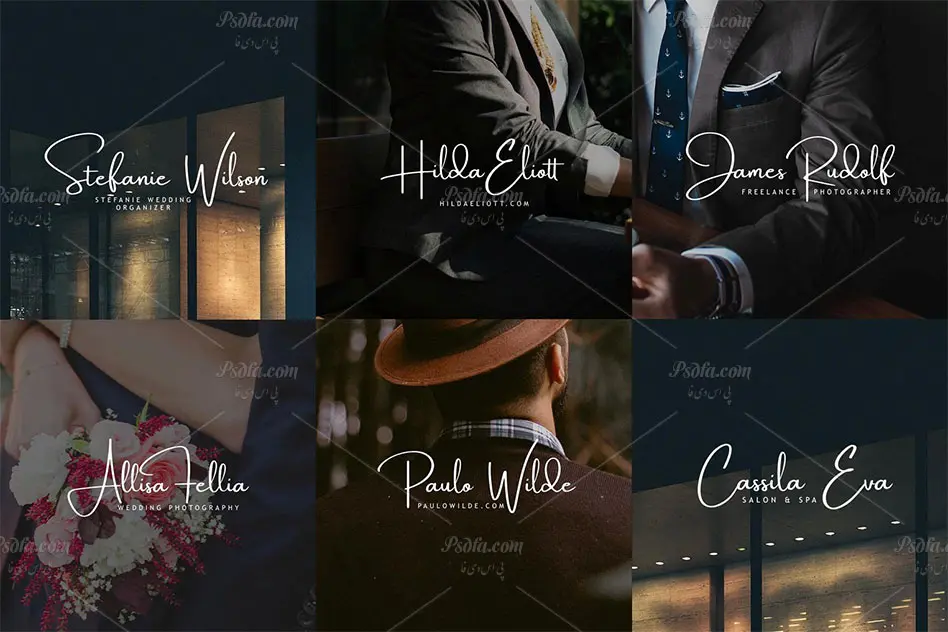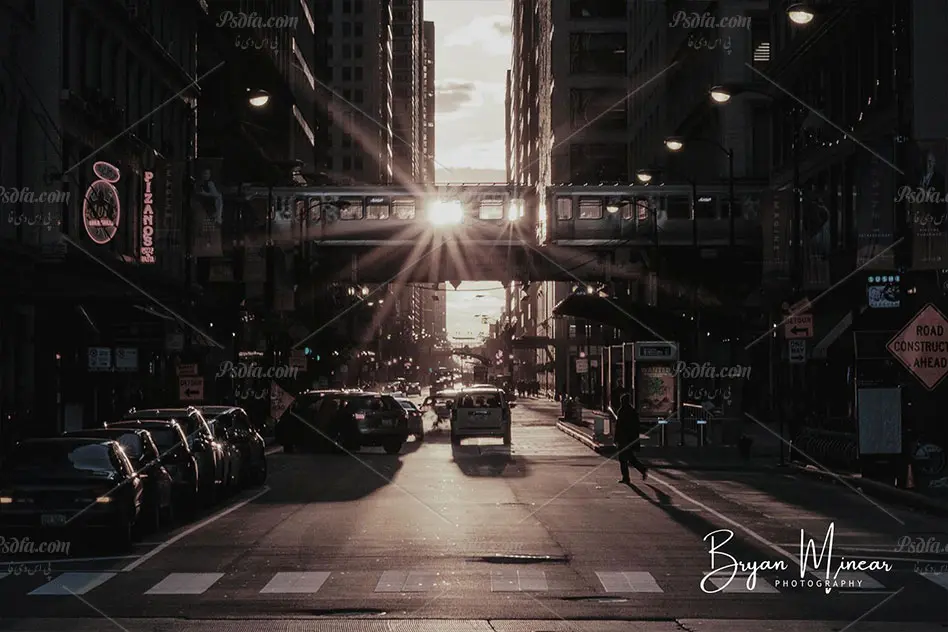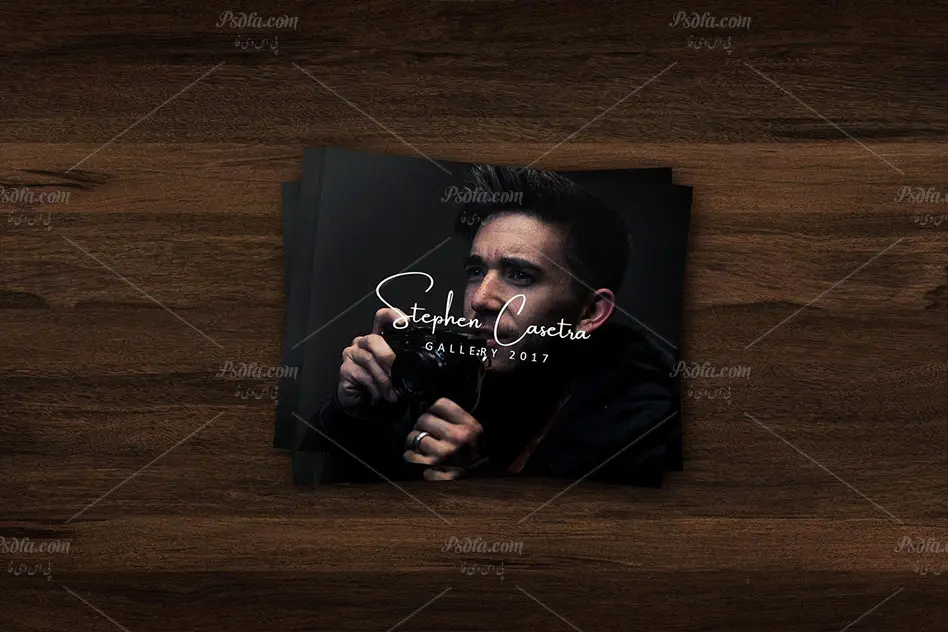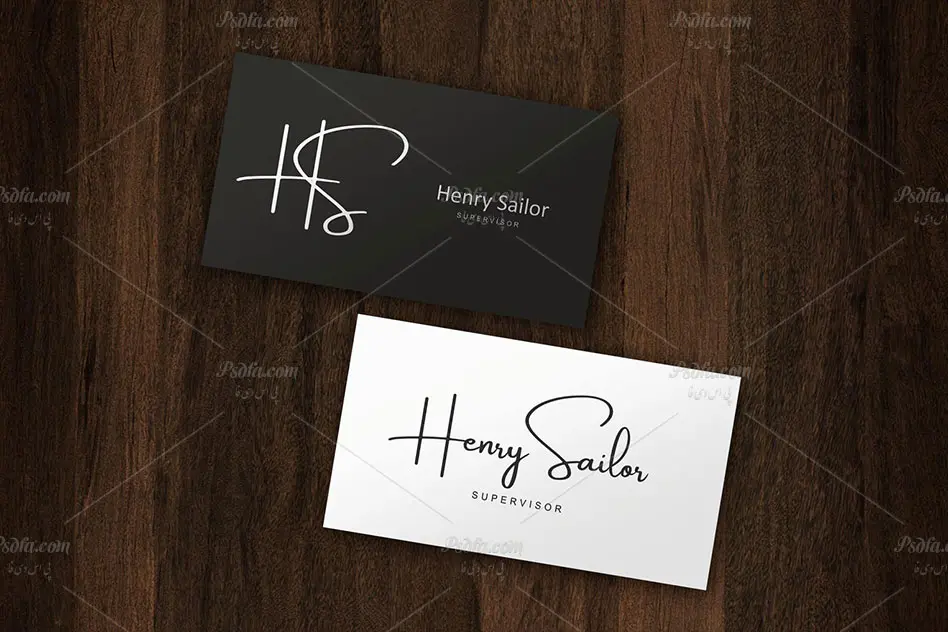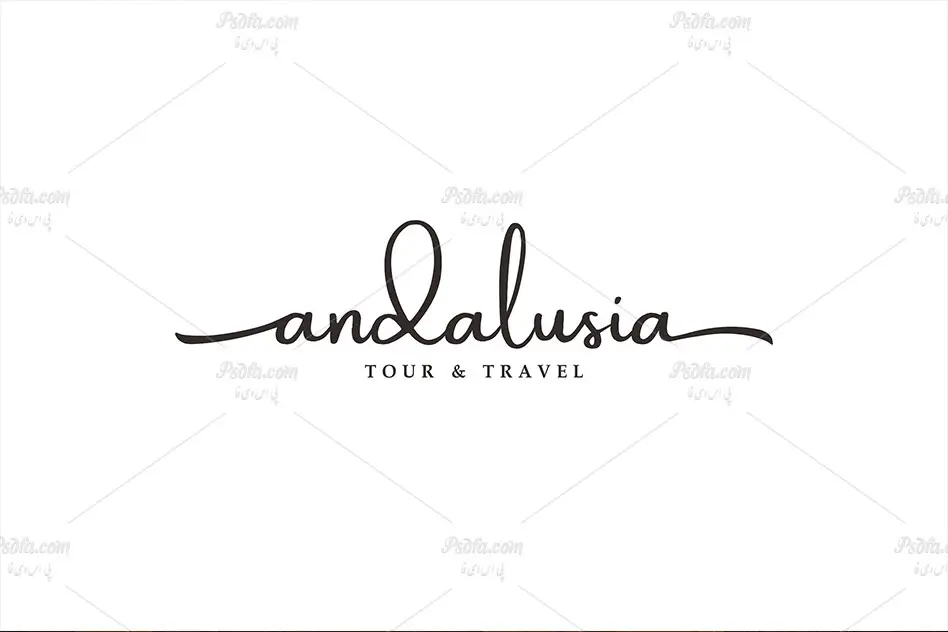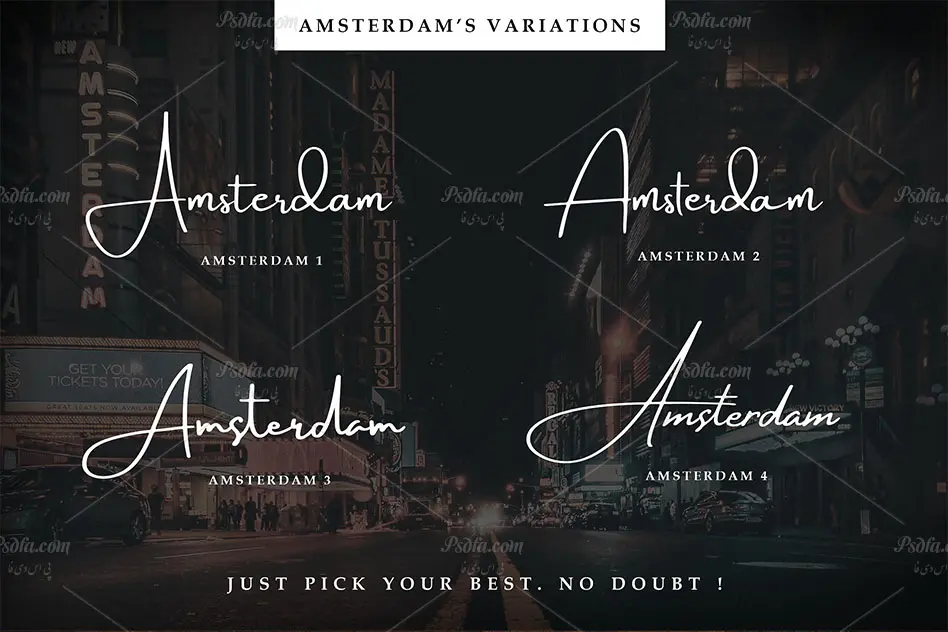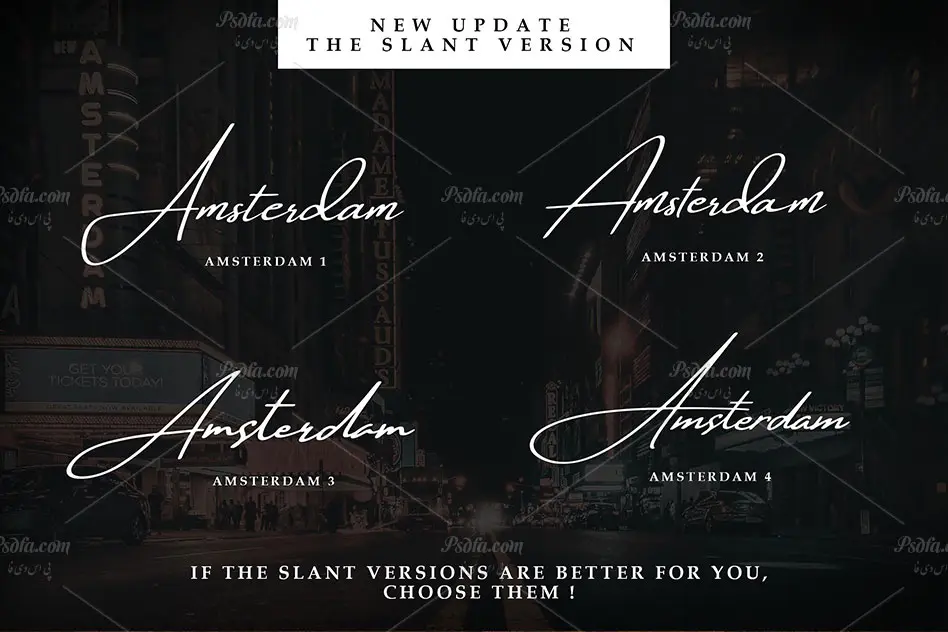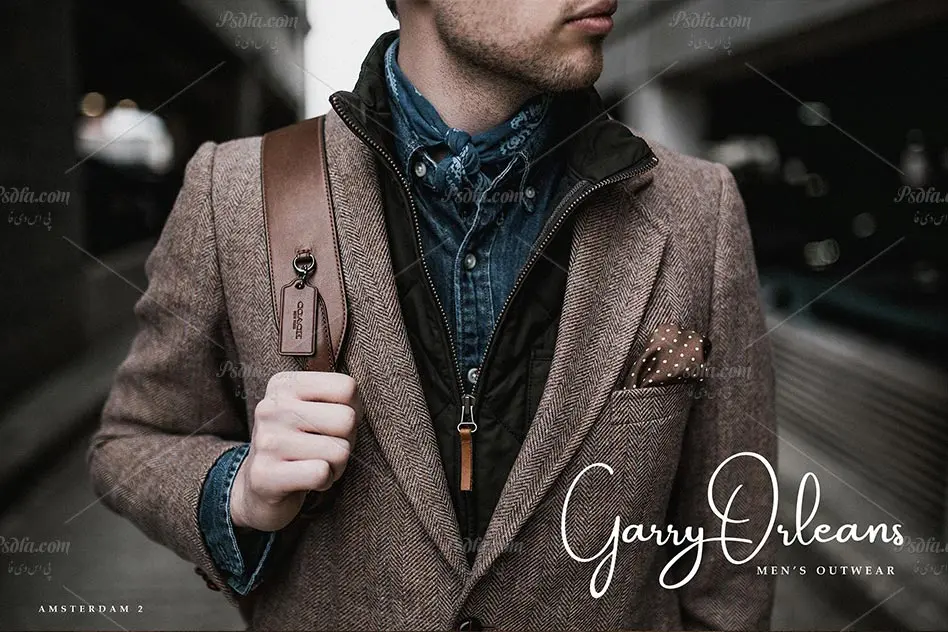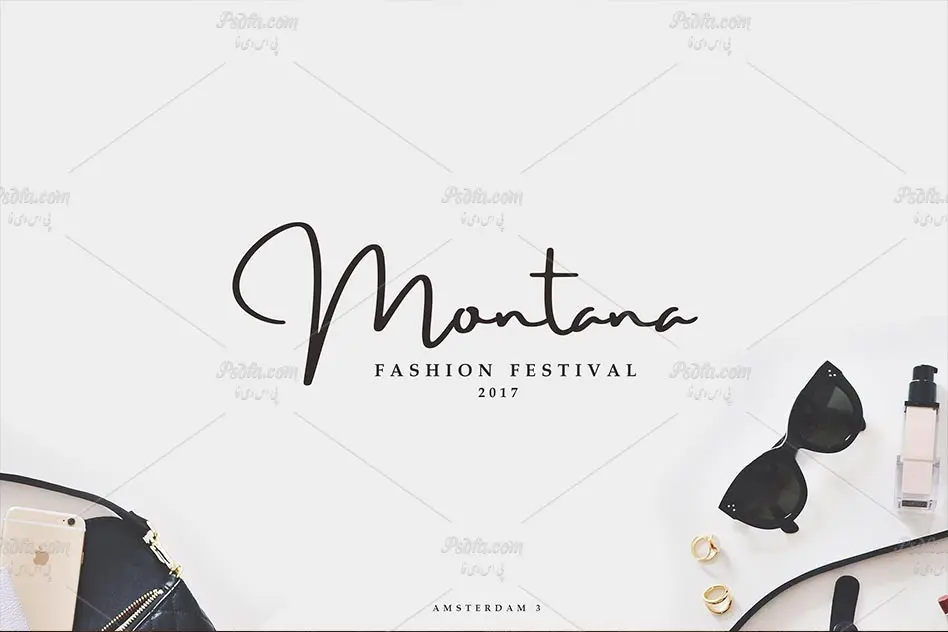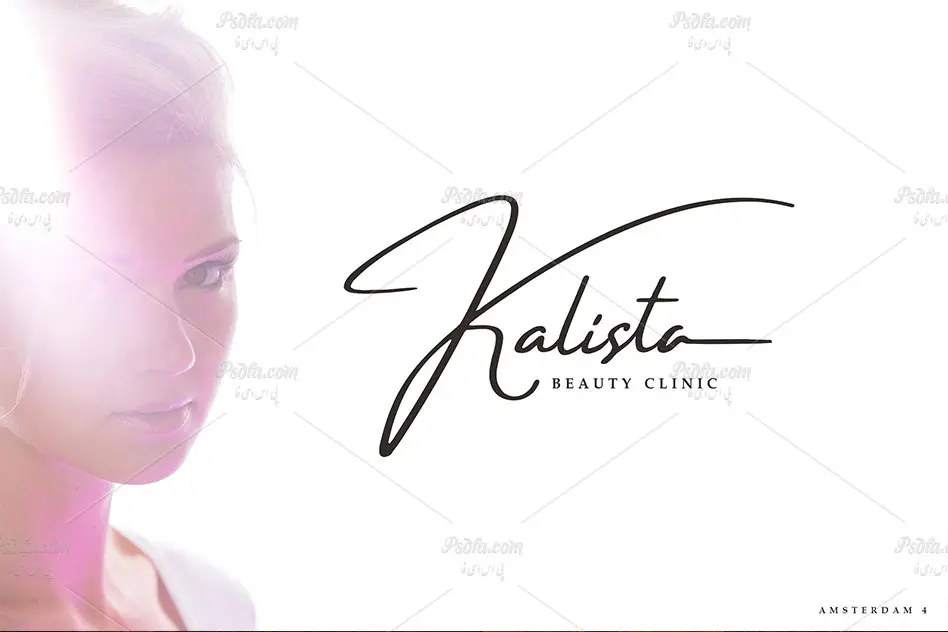
در این مطلب شاهد 8 فونت انگلیسی دستنویس Amsterdam مناسب جهت استفاده در طراحی و گرافیک می باشید. این مجموعه فونت فوق العاده زیبا که از خانواده فونت انگلیسی Amsterdam می باشند در 8 طرح و شکل مختلف و در سه فرمت otf , ttf و Woff در سایت قرار گرفته اند که پس از نصب فونت ها در پوشه فونت های سیستم می توانید از آن ها به طور مستقیم در تمام نرم افزارهای گرافیکی و ویرایشگر متن از جمله نرم افزار فتوشاپ ، مجموعه نرم افزار آفیس و … استفاده کنید.
از این فونت زیبا می توان در طراحی انواع پوستر ، طراحی کارت ویزیت ، طراحی انواع کارت تبریک ، کارت پستال ، کارت عروسی و … استفاده نمود.